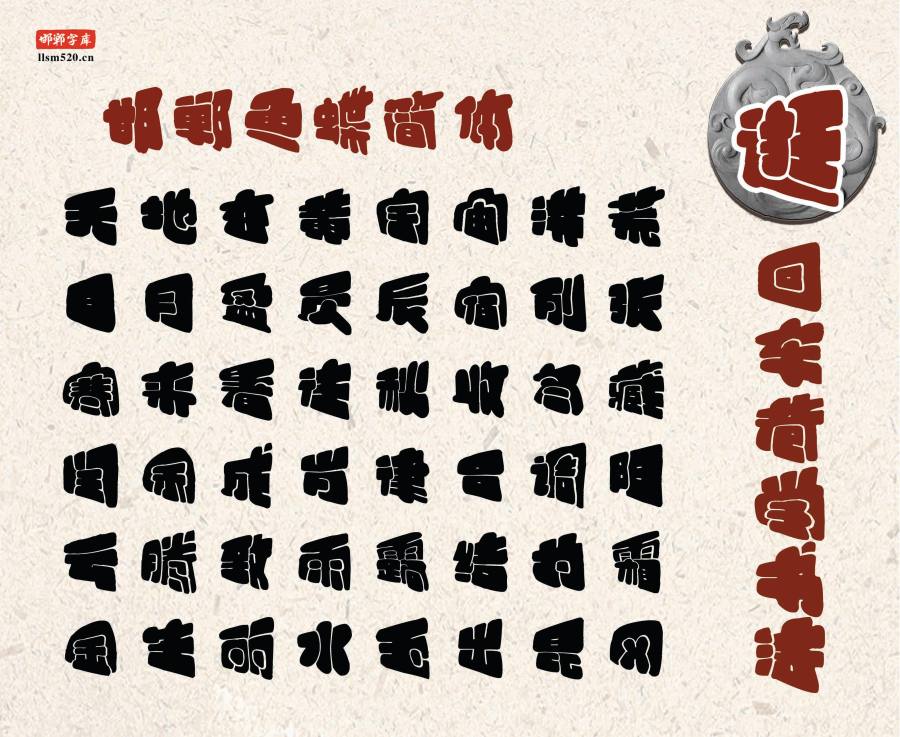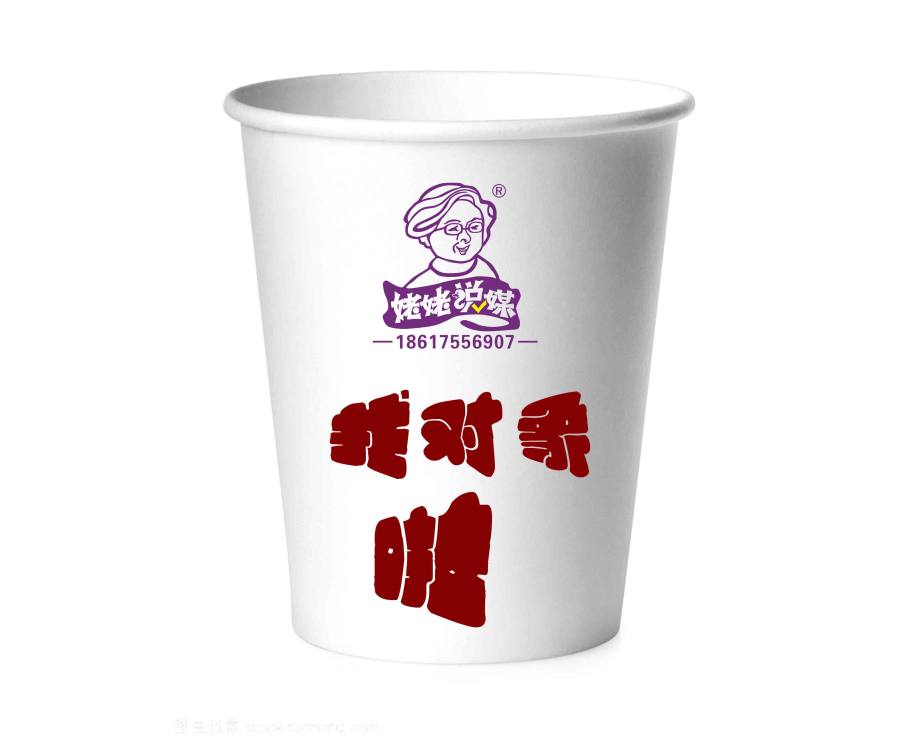
邯郸鱼蝶简体以韩绍杰老师创作的电脑美术字制作而成。该字体笔画粗壮,两端呈圆头,笔画相交紧密,呈凹陷窝状,中宫比较紧凑。黑字面大,字型粗旷,结构严谨,重心一致;外形呈鱼与蝶的翅膀,透视感极强,笔划制作精良,线条刚柔相济,简洁有力。阅读舒适流畅,适用于报刊、杂志和书籍中的大型标题。
邯郸鱼蝶简体,笔画粗状、横竖清晰、突出醒目等特点, 外形呈鱼与蝶的翅膀,透视感极强,有着非常强烈的艺术感。